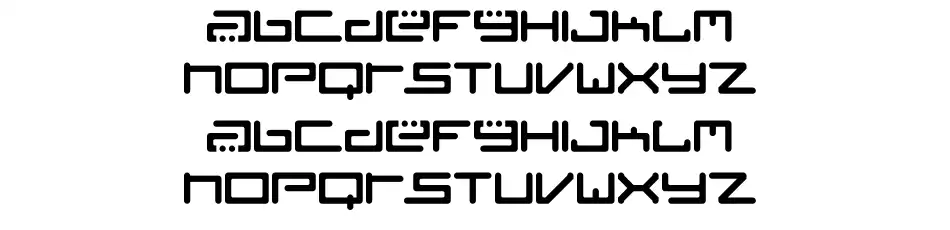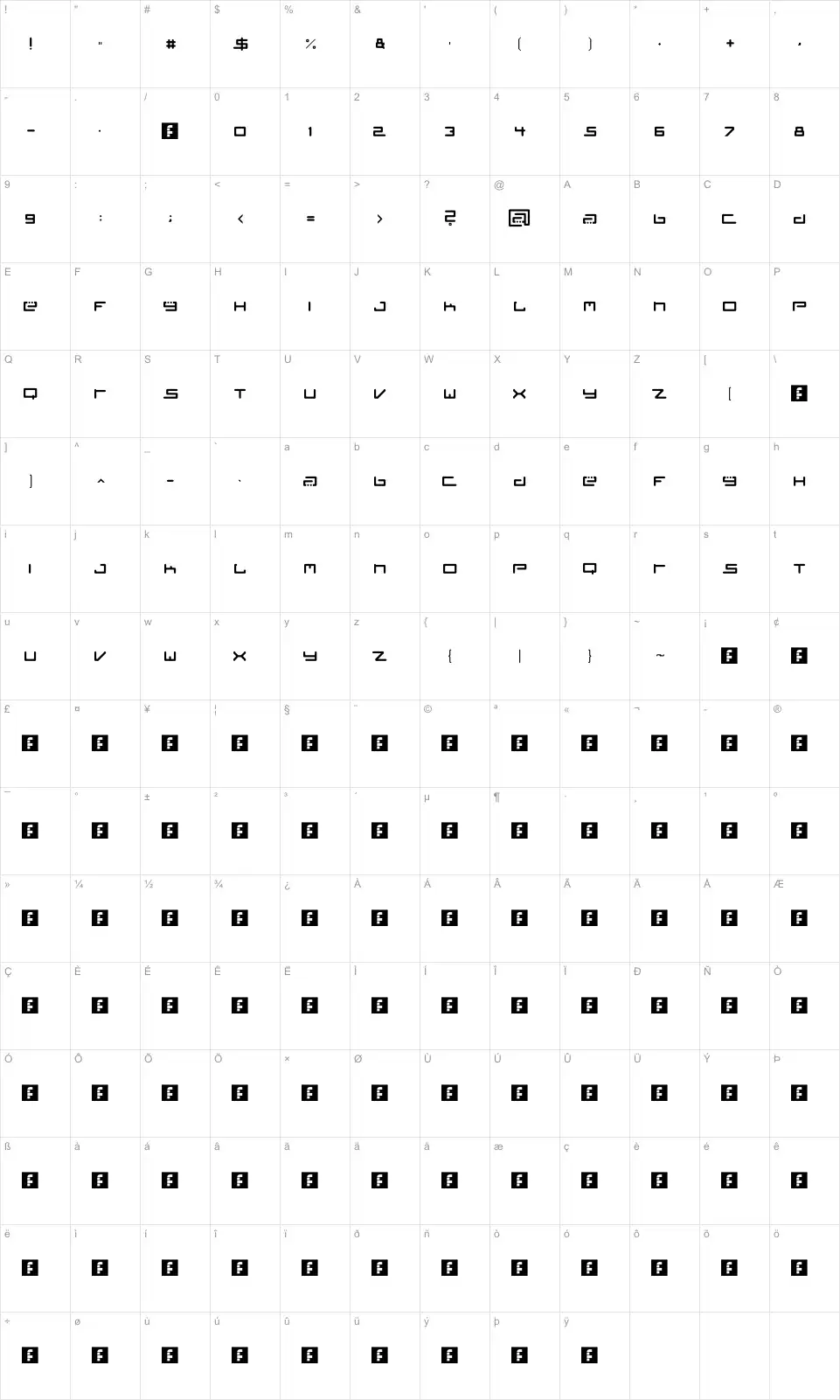
Tiesto Font Regular – Download Grátis
A fonte Tiesto Font Regular, criada por ViNNiE, é perfeita para entusiasmados com o techno e a ficção científica. Esse recurso visual foi adicionado à nossa coleção em 13 de julho de 2022, oferecendo um estilo único e dinâmico. Desenvolvida para o gosto do techno sci-fi, esta fonte TTF é versátil e pode ser usada em designs de tecnologia futurística ou até mesmo em interfaces de jogos de realidade virtual. Se você está procurando por um estilo de fontes que se adequa perfeitamente à categoria de techno sci-fi, esta é a fonte perfeita para você. Além disso, com uma limpa e elegante aparência, ela é simples de usar em qualquer projeto. Os usuários podem baixar o arquivo TTF diretamente ou gerar uma prévia personalizada de texto para ver como a fonte se comportará antes de incorporá-la em seus projetos. Desde a sua disponibilidade, foram instalados cerca de 7540 caracteres da fonte. Seja você um criador de jogos, designer de jogos, criador de conteúdo técnico ou apenas alguém que aprecia a arte e a tecnologia, esta fonte Tiesto Font Regular é uma ótima adição ao seu arsenal de recursos.